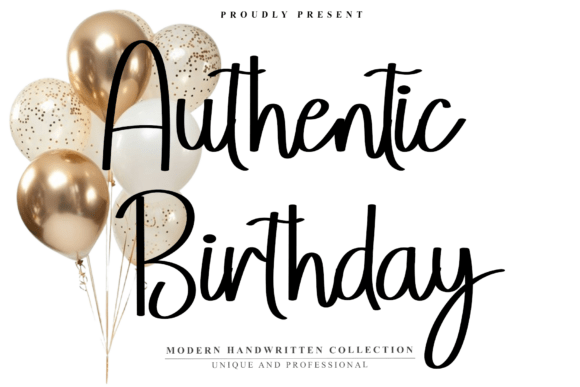
Authentic Birthday
Việc tìm kiếm các thành phần thiết kế phù hợp có thể là một thách thức, nhưng Authentic Birthday cung cấp một bộ sưu tập đặc biệt giúp nâng tầm công việc của bạn ngay lập tức.
Được chế tác với độ chính xác cao, Authentic Birthday cung cấp các vector sạch, kiểu chữ mượt mà và giấy phép thương mại để bạn yên tâm.